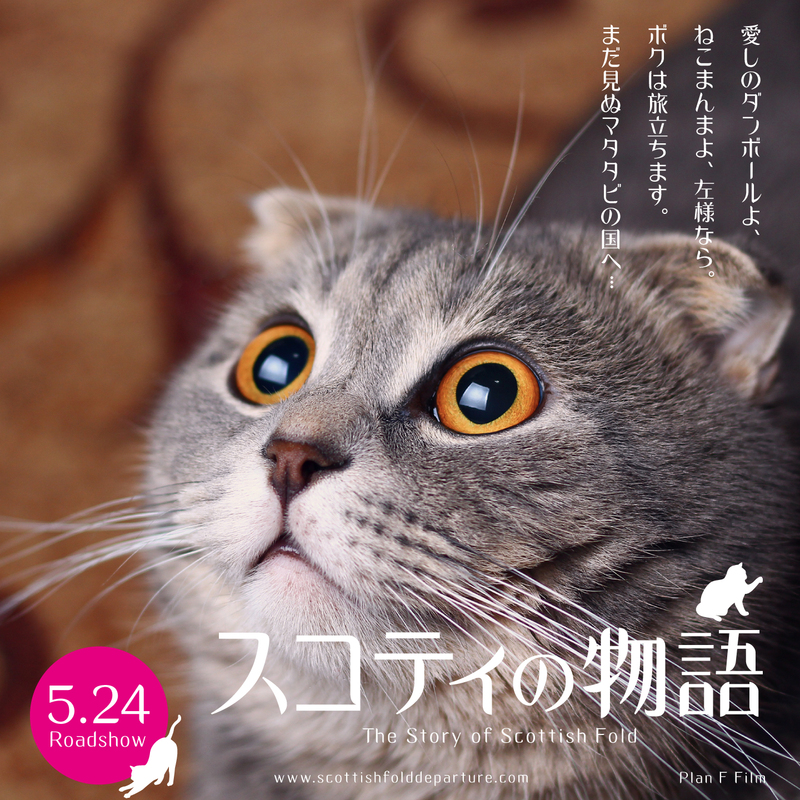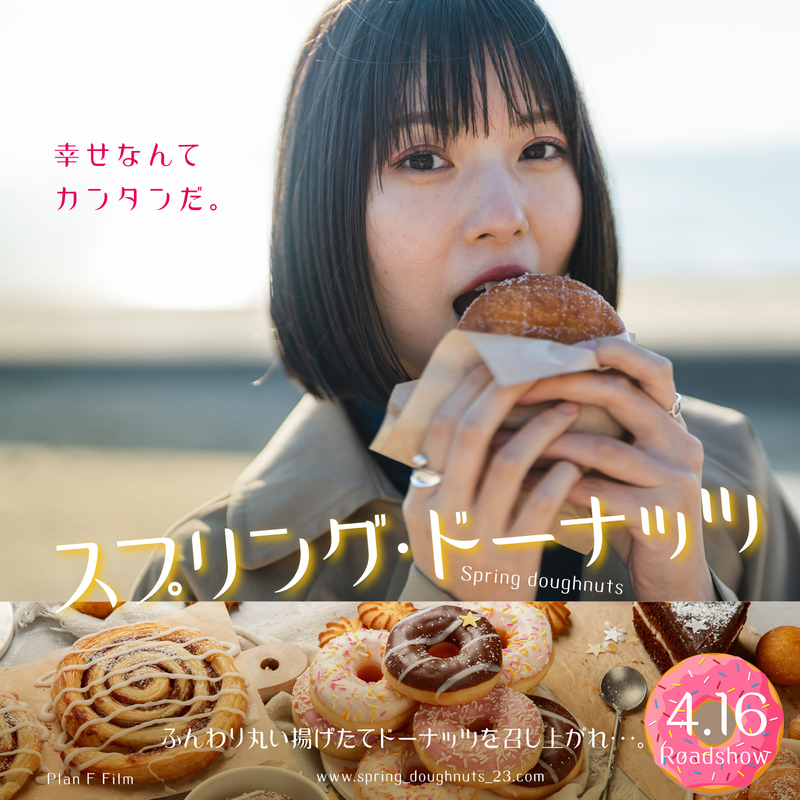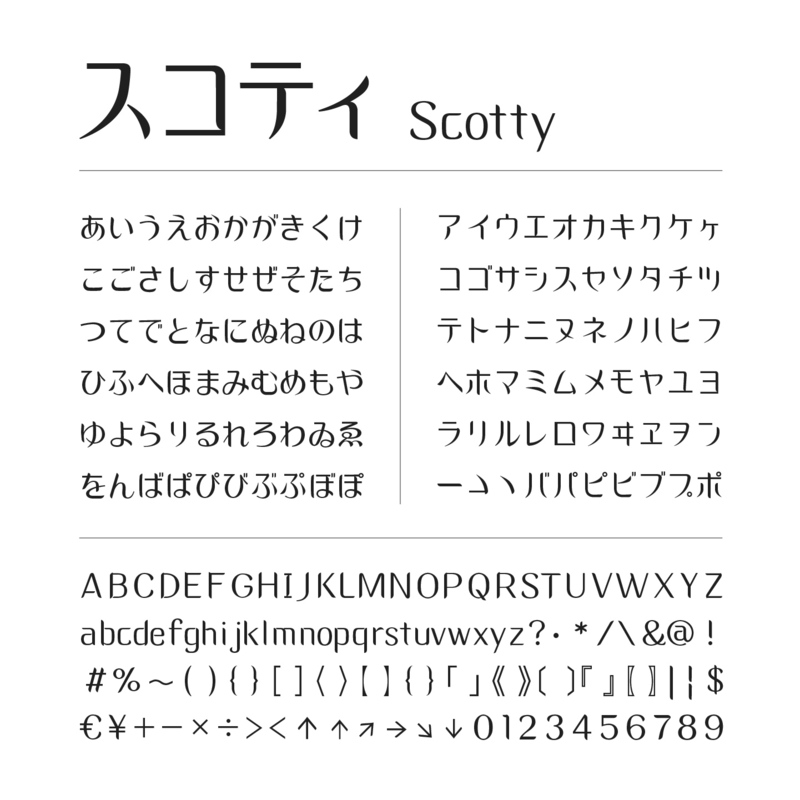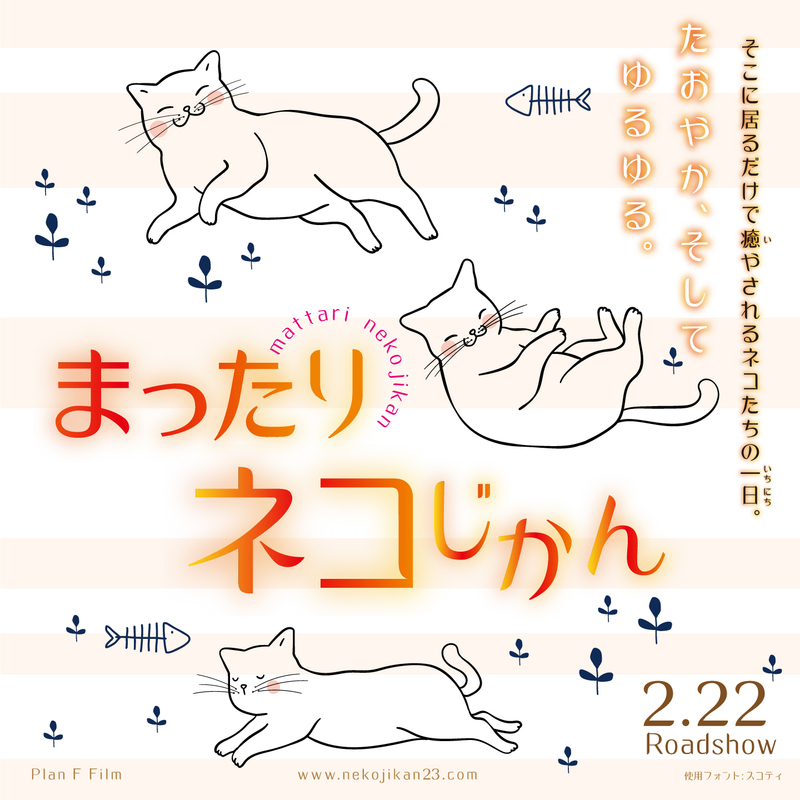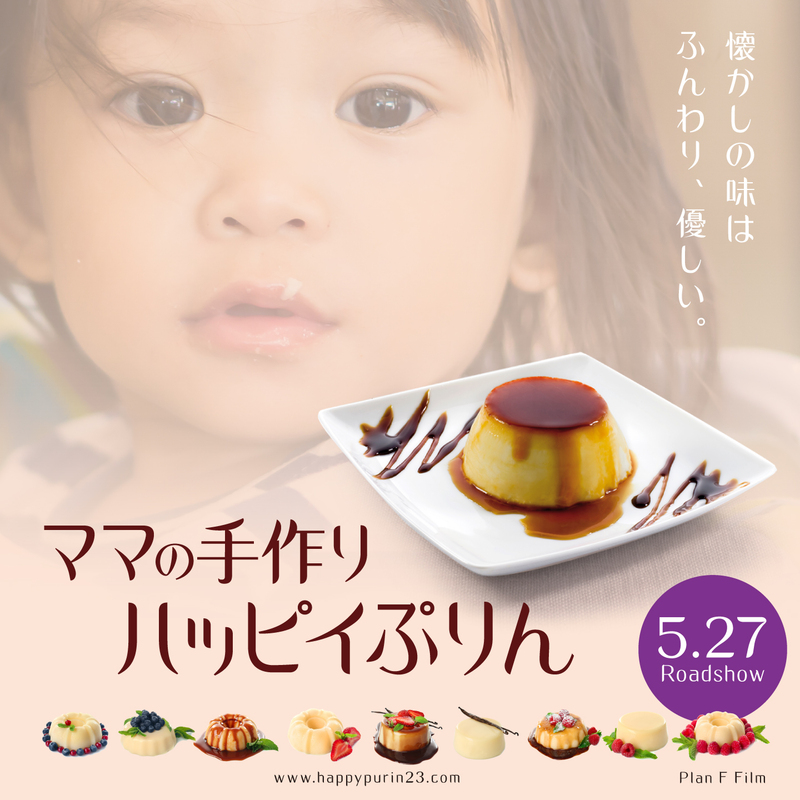
スコティッシュフォールドの耳のような、ちょっとかわいいイメージで作成しました。
春の日を思わせる優しくゆるやかな雰囲気のフォントです。
視覚的な楽しさだけでなく、実用性も兼ね備えており、ショップのロゴ、POPの作成など大小さまざまなプロジェクトに使用することができます。
【かな版】には、かな、アルファベット、数字、約物。漢字は教育漢字1006字を収納。アウトライン抽出可。収録文字数1520字。